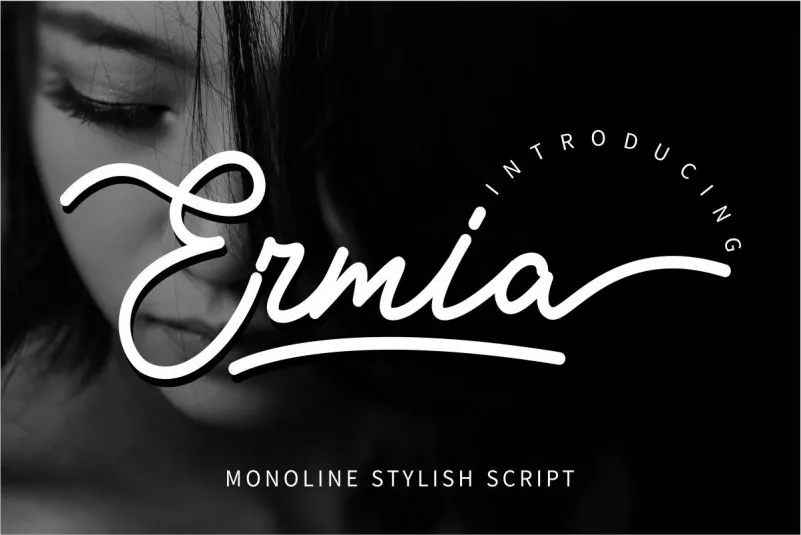
Ermia Font é uma elegante fónta à mão escrita projetada pela GFR Creative para ser usada no estilo moderno. Perfeita tanto para trabalhos de marca, como logotipos e designs de embalagens, quanto para o design gráfico, publicidade ou invitations, esta fonte irá tornar seu projeto único e impecável. Inspirada nos luxos e marcas, Ermia oferece inúmeras opções de usos criativos que podem revolucionar suas necessidades de design. Seja para a criação de logotipos, criação de embalagens sofisticadas ou até mesmo para designs de eventos especiais, Ermia é uma escolha ótima para qualquer projeto que precise de conteúdo escrito à mão. Se você está buscando adicionar um toque de elegância e originalidade a seus projetos, Ermia Font é uma opção perfeita.